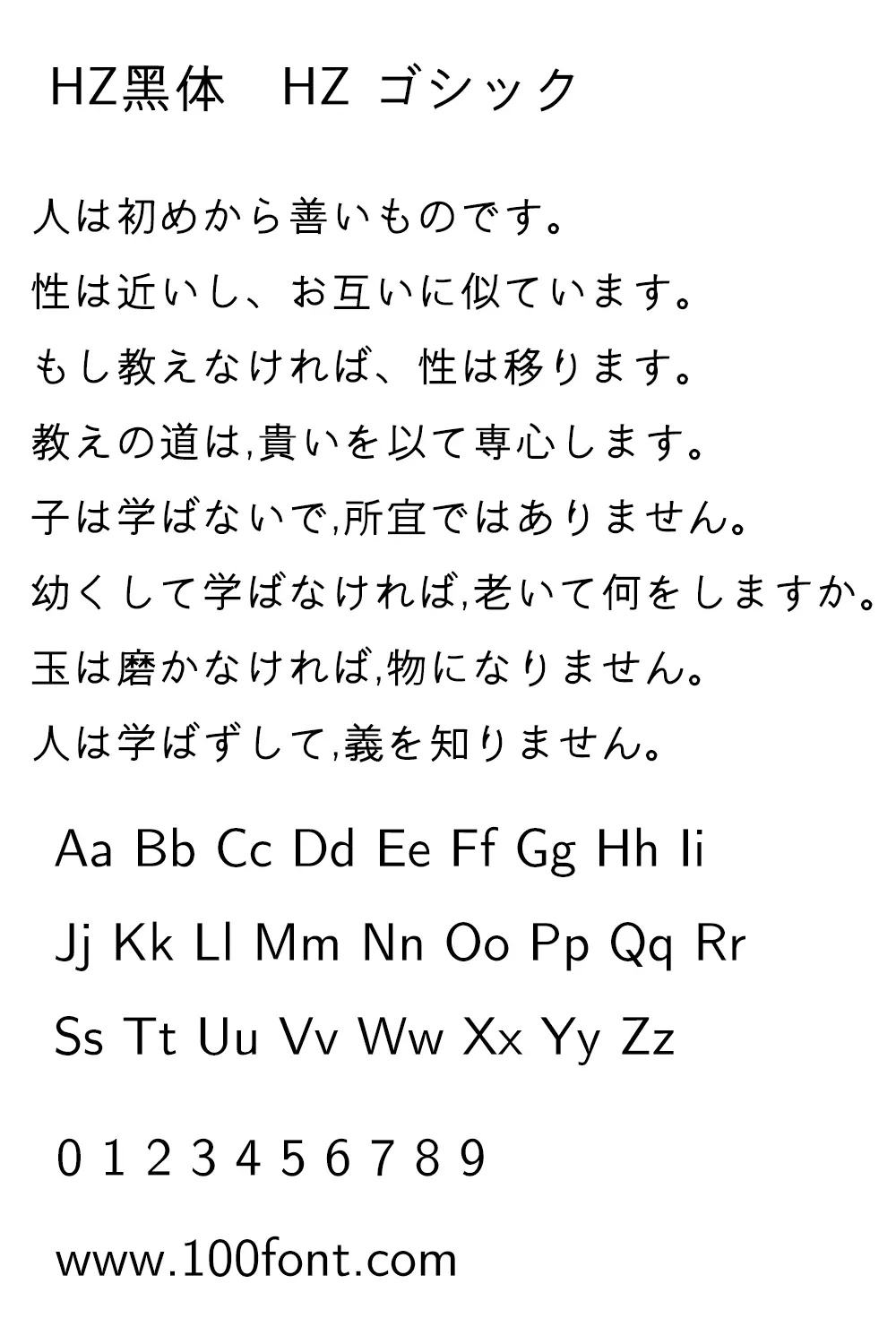
這是一個免費的OpenType cid的日文字體,來自字形維基(GlyphWiki)的CJK數據,有5個字重。
拉丁文、希臘文和西裡爾字母並非源自字形維基(GlyphWiki),而是源自Computer Modern Unicode,因為GlyphWiki的Kage引擎是為中文字符設計的。
一些符號來自M+字體和GL Antique字體。
This is a free/libre OpenType CID-keyed Japanese font derived from GlyphWiki's CJK data, with weight variations.
Latin, Greek and Cyrillic glyphs are not derived from GlyphWiki but from Computer Modern Unicode because GlyphWiki's Kage engine is intended for Chinese characters and not good at LGC.
Some symbols are from M+ fonts and GL Antique font.